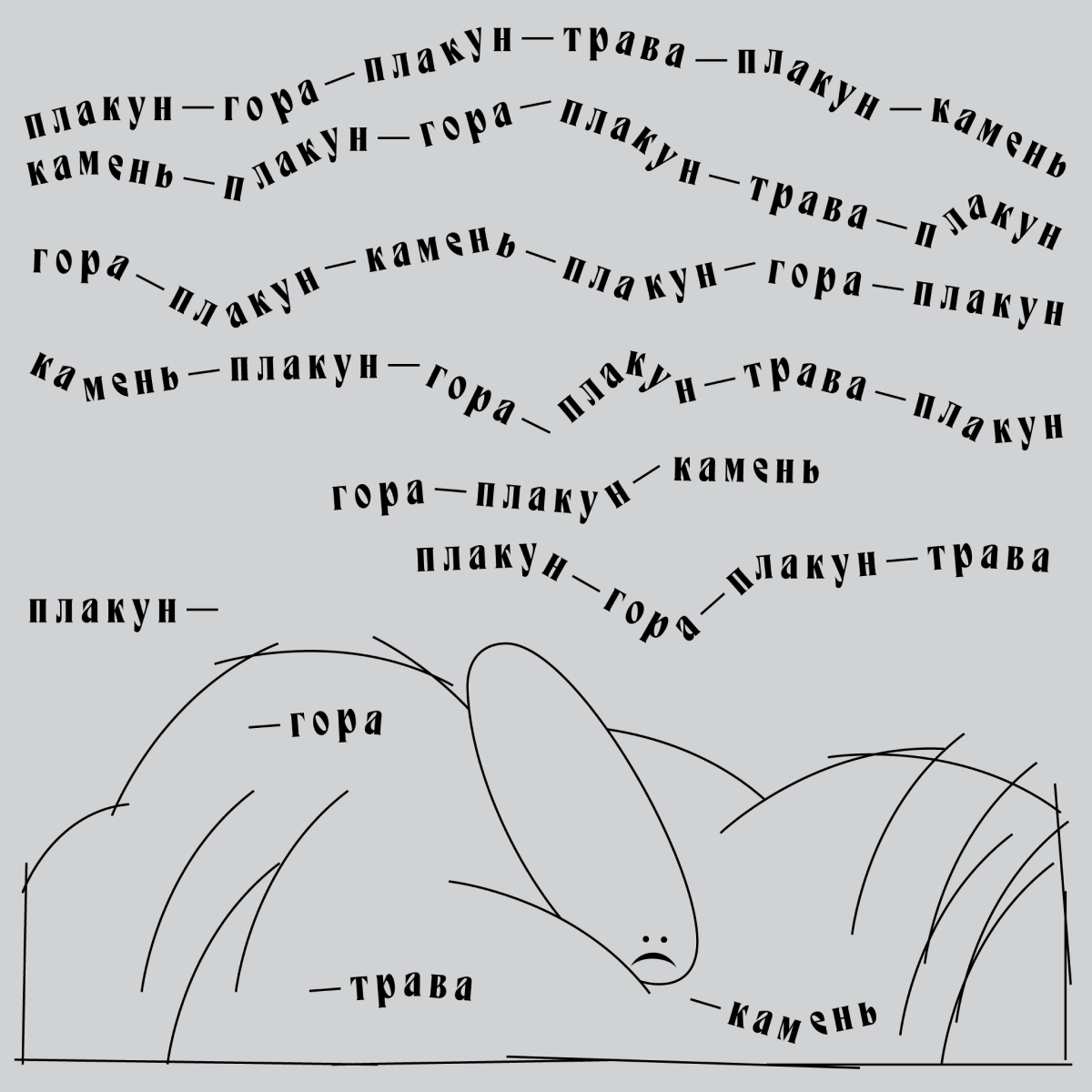
Время от времени дизайнер Владимир Коломейцев присылает в телеграм-чат Playfaces надпись и предлагает участникам сделать леттеринг на её основе. Одна из таких
Надпись с обложки книги 1917 года
Смешав характер исторического прототипа с современной каллиграфией и пластикой шрифтов ар-нуво, Agse вырос в динамичную узкую антикву с экстремально наклонёнными овалами, качающимися в разные стороны, и цепкими вертикальными засечками.
Agse — заголовочный шрифт, который хорошо работает в паре с более спокойной текстовой антиквой или гротеском. Он не боится экспериментировать и будет отлично смотреться с тенями или обводкой.
Автор Agse — Елена Новосёлова, шрифтовой дизайнер, художник-график и преподаватель. Училась в шрифтовой мастерской Александра Тарбеева, работала его ассистентом. Сейчас преподаёт шрифт в школе дизайна ВШЭ, работает над шрифтовыми проектами как фрилансер.